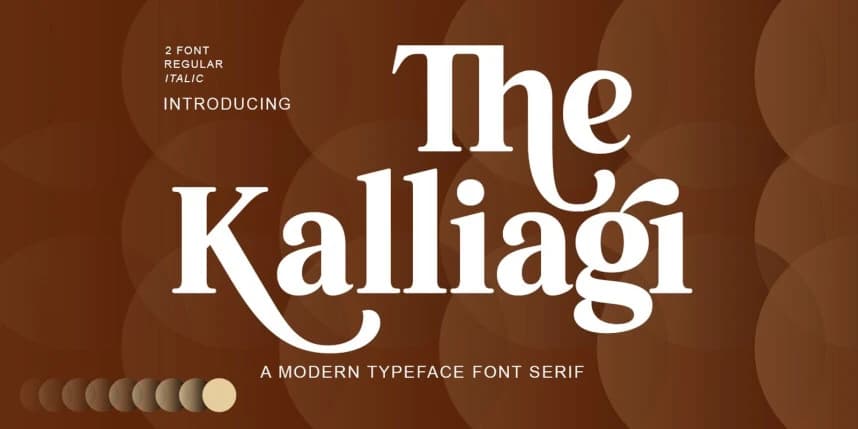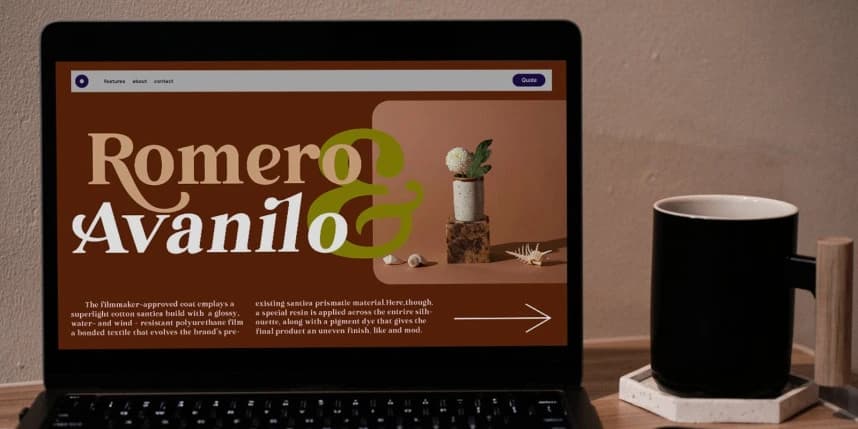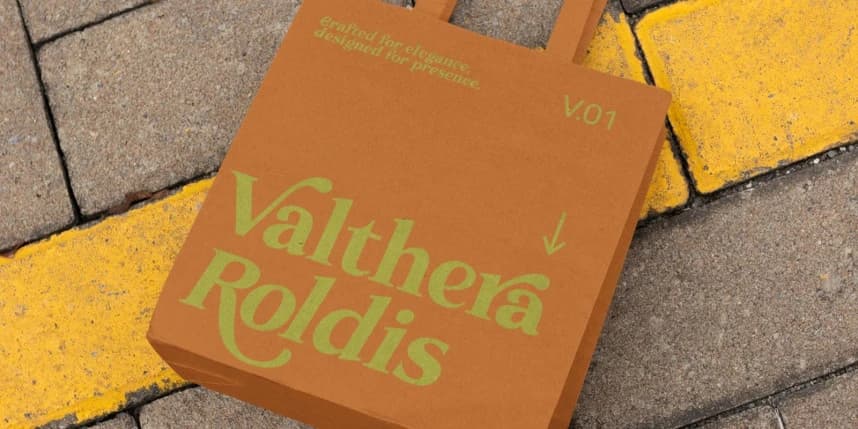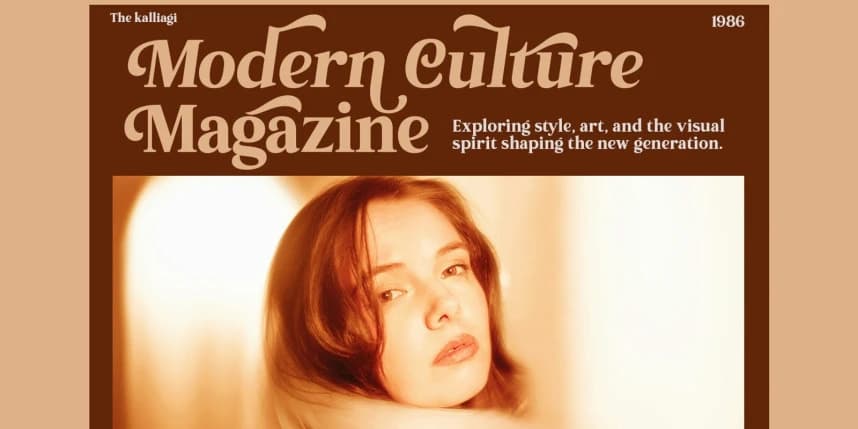
Kalliagi Yazı Tipi
The Kalliagi Font, lüks, zarif, modern, benzersiz ve şık bir görünüme sahip bir serif yazı tipidir. Bu yazı tipi özellikle lüks temalı projeler, marka oluşturma projeleri, dergiler, sosyal medya, logolar ve web sitesi başlıkları için tasarlanmıştır.
The Kalliagi Font, lüks, zarif, modern, benzersiz ve şık bir görünüme sahip olan bir serif yazı tipidir. Bu yazı tipi özellikle lüks temalı projeler, marka kimliği projeleri, dergiler, sosyal medya, logolar, web sitesi başlıkları için tasarlanmıştır
The Kalliagi